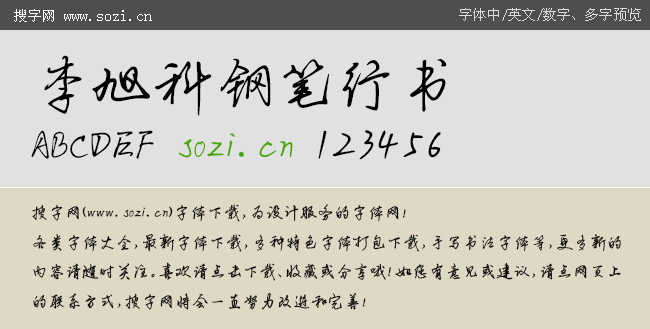
李旭科鋼筆行書(shū)
搜字網(wǎng)提供一款李旭科鋼筆行書(shū)中文書(shū)法字體下載,李旭科鋼筆行書(shū)是一款非常實(shí)用的中文行書(shū)字體,該字體線條粗細(xì)適中,字形飄逸大方得體,整體風(fēng)格非常的出色,可用于藝術(shù)設(shè)計(jì)、包裝印刷、簽名設(shè)計(jì)、圖形設(shè)計(jì)等領(lǐng)域。